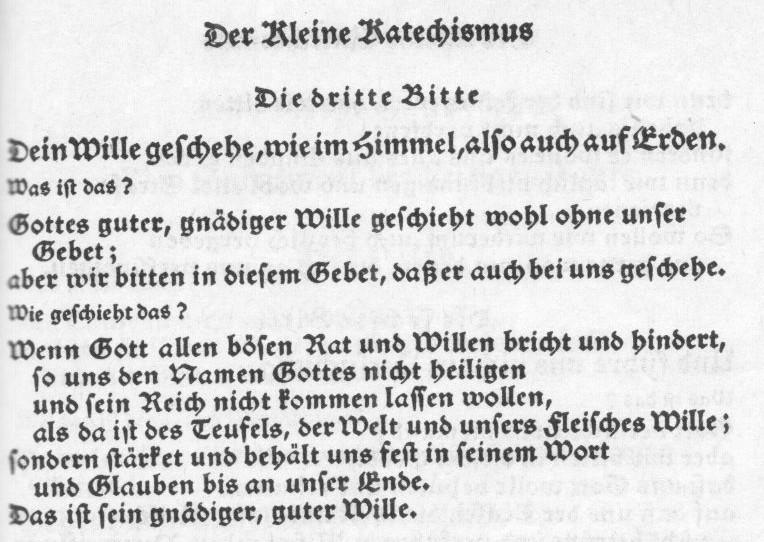
Und hier ein paar Anmerkungen meinerseits:
1. Hat es einen Grund, dass manchmal die Zeilenabstände geringer sind? (Beispielsweise haben in Artikel 3 die Zeilen 3-5 einen geringeren Abstand zueinander als die Zeilen 1-3).
2. Die Bibelstellen kommen meiner Erfahrung nach zur besseren Verwendung entweder direkt zu den Bezugsstellen, etwa so wie beim Bekenntnis von Westminster oder an einer Randspalte, wie in der Weimarer Ausgabe der Werke Luthers etwa im großen Katechismus, letzteres aber eher, wenn die einzelnen Artikel länger sind als im vorliegenden Text.
3. Sind die Anmerkungen historisch bzw. mitübersetzt (und somit „Teil des Textes“) oder vom Übersetzer hinzugefügt? Falls letzteres der Fall sein sollte (was ich vermute), müssten sie meiner Meinung nach besser vom eigentlichen Bekenntnistext abgesetzt werden.
4. Der „ursprüngliche Titel“ (also der ganze kursive Text auf Seite 3) wirkt für mein Gefühl etwas unpassend, ich würde ihm entweder eine  separate Seite geben, oder ihn mit auf die vorangegangene Seite stellen.
1. Ja. Der Text der Artikel ist in Sinnabschnitte aufgeteilt, wo diese eine Zeilenlänge überschreiten, werden die Zeilen eines Sinnabschnittes zusammenhängend ohne den erhöhten Abstand gedruckt. Offenkundig ist das nicht hinreichend deutlich geworden. Hast Du eine Idee dazu? Ich hatte mit Bulletpoints experimentiert, aber die Resultate waren, obschon verdeutlichend, ästhetisch unbefriedigend.
2. Zustimmung, aber noch nicht für diese Ausgabe. Eine Veröffentlichung im Druck ist (bei hinreichendem Interesse, und mit etwas Zusatzmaterial) vorgesehen, vermutlich mit Randspalte, evtl. auch mit Fußnotenbuchstaben, vermutlich eher nicht mit Klammern im Fließtext. Allerdings ist da noch reichlich redaktionelle Arbeit erforderlich, um die Stellen den Textpassagen ganz präzise zuordnen zu können - im Original ist bei den Randspalten z.T. etwas geschlampt worden, und die modernen englischsprachigen Ausgaben haben sie alle nur (wie ich aktuell auch noch) lieblos an die Artikel angehängt. Es müssen also alle Belegstellen im Abgleich mit dem damaligen Druck erneut durchgesehen werden (inhaltlich ist das schon mal erfolgt) und dann zugeordnet.  Ich gelobe Besserung, aber erst später ;-) Das jetzt aktuelle Anliegen betrifft im Grunde eine Vorschau oder Vorabveröffentlichung, und es ist erforderlich, dass der Text selbst nächste Woche erste Interessenten erreichen kann.
3. Auch richtig, daher wird im Lorem-Ipsum Teil hinten (Hinweise zur vorliegenden Textfassung) stehen:
Die vorliegende Deutsche Fassung von 2016 enthält [...].
Sie enthält nicht die Widmung (an die Abgeordneten des englischen Parlaments), die Vorrede, das Schlusswort und die drei ursprünglichen Anmerkungen: zu Artikel 16 (eine Sammlung christologischer Bibelstellen), zu Artikel 40 (zur Wortbedeutung des gr. baptizo und zur Wahrung der Schicklichkeit bei der Taufhandlung) und zu Artikel 48 (eine politische Definition der rechtmäßigen Obrigkeit im England des Jahres 1646 und ein Appell an diese zu gottgefälligem Handeln).
Stattdessen sind drei neue Anmerkungen zu Artikel 39 (Abfolge von Taufe und Mahlfeierteilnahme), zu Artikel 42 (Vollmacht der örtlichen Gemeinde in Mitgliedschaftsfragen) und zu Artikel 45 (Lehrdienst) aufgenommen.
Die neuen drei Anmerkungen sollen aufgrund eines Gremienbeschlusses (so wie es 1646 die jetzt nicht mehr aufgenommenen ursprünglichen drei Anmerkungen waren) Teil dieser Textausgabe sein. Dass es eine Ergänzung ist, muss man natürlich dokumentieren und offenlegen.
4. Schau ich mir an. Aufgenommen werden soll er auf jeden Fall, im Anhang wird auf ihn Bezug genommen, aber vielleicht ist er nicht an der bestmöglichen Stelle untergebracht.
Ich find Bold für die Überschriften ein bischen heftig bei der Menge Weißraum.
Für eine gute Lösung hielte ich Einrückungen, wie etwa im Fließtext auf der unteren Hälfte des von Dir gezeigten Titelblatts oder  folgenden Beispiel von Luthers kleinem Kathechismus:
(EKG 1965, Ausgabe Thüringen, S.41)
Es ging mir dabei nicht um quellenkritische oder theologische Fragen, wegen denen eine Dokumentierung nötig wäre, sondern um eine äußerliche: Im Moment wirken die Anmerkungen rein optisch zu sehr wie ein Teil des Textes (ins Besondere bei Artikel 45, wo die Anmerkung länger als der Text ist), vielleicht wäre es besser, wenn man diese Anmerkungen entweder
Danke für die Bändigung des Grimmes! Vielleicht ziehst du zweispaltigen Satz in Erwägung? Blocksatz in A4 auf volle Satzbreite lädt nicht zum Lesen ein. Oder die Kolumne wird deutlich verschmälert mit sehr breiten Rändern, was auch eine weitere Erinnerung an die Vorlage mit sich bringen könnte. Die Absätze sollten, außer dem ersten, Gevierteinzüge bekommen.